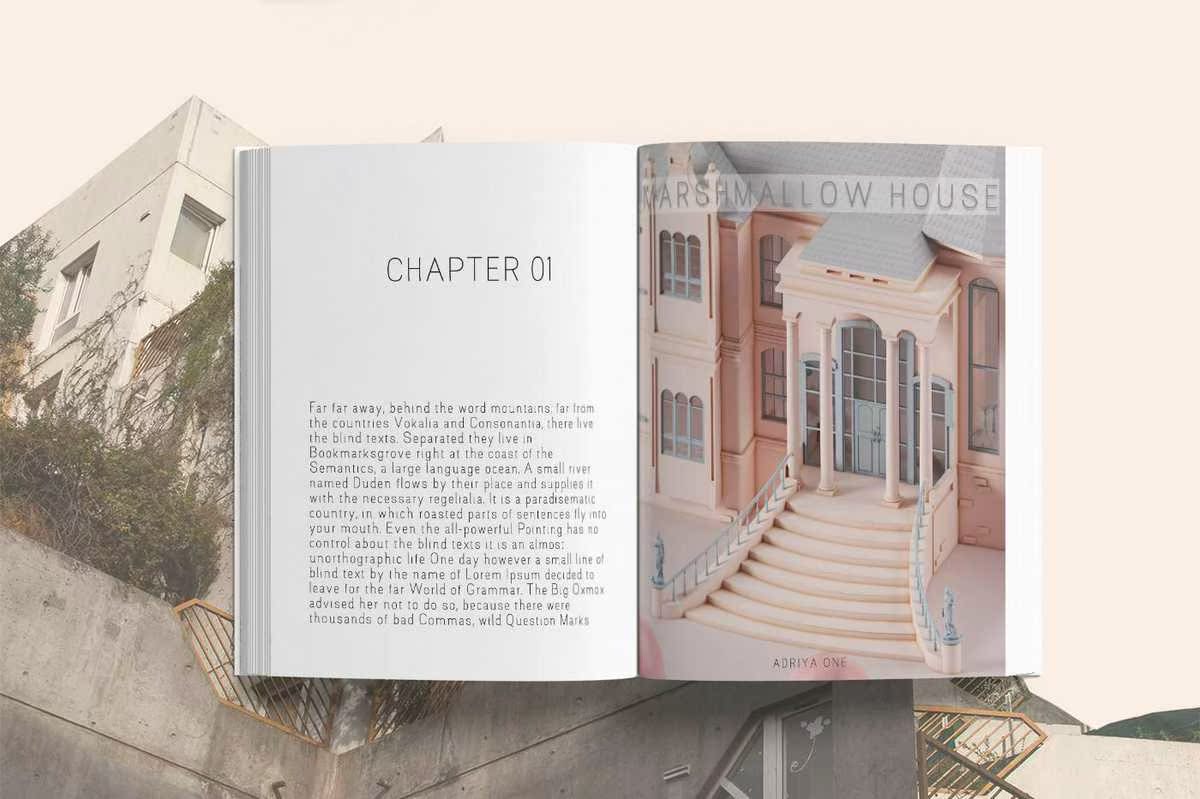
MAGNOLLAISANELEGANTAND和CLEANSANSERIFONT。它是专为强大、现代化的零售业而设计的系列产品。MAGNOLLAISANELEGANTAND完美适用于任何品牌、徽标、杂志、视频、婚礼、报价、印刷、产品包装、网站、服装设计等。MAGNOLLAISANELEGANTAND和CLEANSANSERIFONT。它是专为强大而设计的系列产品,现代品牌、标志、杂志、视频、婚礼、报价、印刷、产品包装、网站、服装设计等方面的完美。